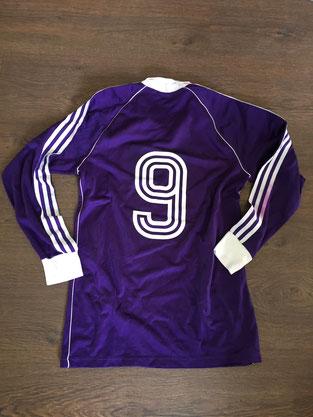
70er Jahre Rückennummern
ich suche die Schriftart, wie auf dem Foto dargestellt, welche in den 70er Jahren als Rückennummern auf Fußballtrikots verwendet wurde. Auch eine ähnliche Schriftart würde mir helfen. Ich benötige diese für aktuelle Trikots im Retro - Style.
wenn das trikot wirklich aus den 70ern ist, mach ich dir da nicht viel hoffnung das du einen font findest. das ist ja pre DTP und wer weiss wie die zahlen damals entstanden sind. hast du mehr beispiele?
ähnliche fonts findest du sicher unter dem begriff triline oder multi-line, hier ein paar beispiele:
gibts auch ohne 3d-effekt
Diese Adidas Retro Fonts sehen deinem Muster-Shirt schon verdammt ähnlich. Der Blog scheint noch aktiv zu sein, vielleicht lohnt sich eine Mail? Auf Pinterest wurden sie auch fleißig gepostet.